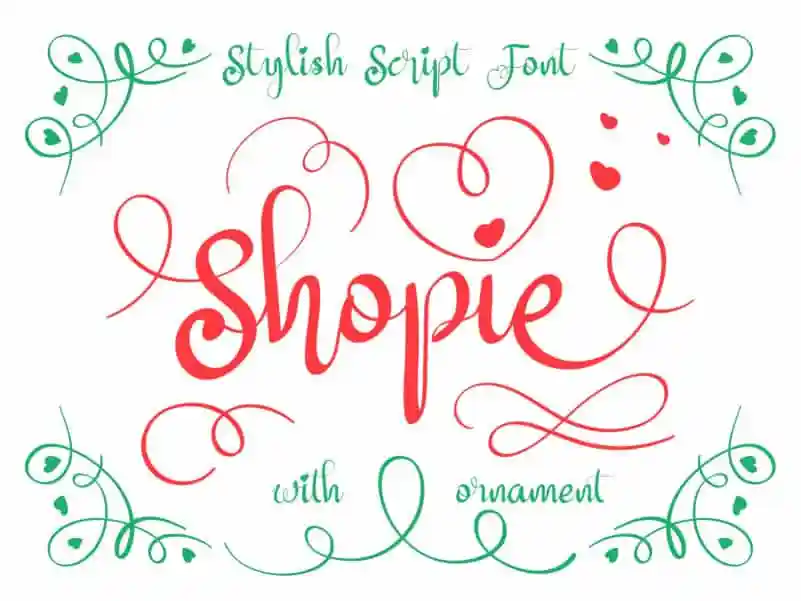
Shopie Calligraphy Font – Download Grátis
A Shopie Calligraphy Font é uma deliciosa tipografia script com traços arredondados, perfeita para quem busca personalidade em seus projetos digitais. Esse elemento adicional não apenas adiciona um toque refinado ao seu design, mas também proporciona harmonia e variedade sem deixar o texto sem estrutura ou redundância. O resultado é uma fonte que reflete a delicadeza necessária para expressar sentimentos e histórias através de textos elegantes. Ideal tanto para anúncios digitais quanto para letras pequenas em design editorial, a Shopie Calligraphy Font surge como um companheiro perfeito para quem busca criar mensagens impactantes e personalizadas. Não há dúvida de que essa fonte é uma opção ideal para designers apaixonados por trabalhar com estilos script delicados e elegantes.